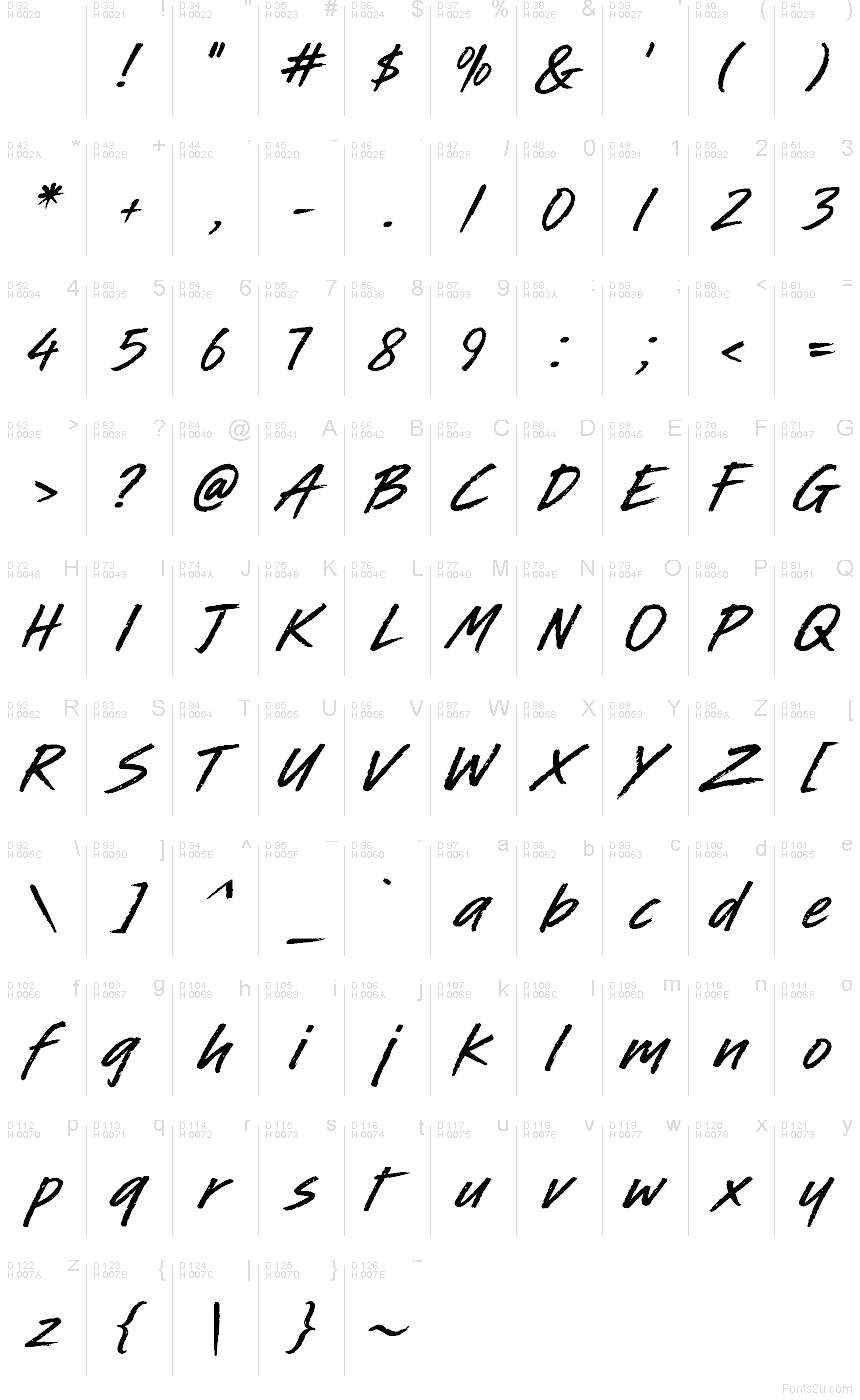
Style your Lipstick
Style Your Lipstick من تصميم CAT.B هو خط مجاني بأسلوب الفرشاة (Brush Script)، يتميز بضربات سريعة وملمس جاف ومكسور يمنح الحروف طابعاً خاماً وغير مصقول. تمنحه الحواف الخشنة والخطوط المتلاشية إحساساً يشبه الكتابة بأقلام الماركر أو فرش المكياج، مع تنوع كافٍ يجعل النص يبدو حيوياً وديناميكياً.
تتناسب هذه الحيوية التجميلية بشكل مثالي مع أغلفة أحمر الشفاه، وتصاميم الجمال، وعلامات البوتيك التجارية، وعناوين المدونات، وبطاقات الاقتباسات على وسائل التواصل الاجتماعي. ولأن أثر الفرشاة يبدو باهتاً قليلاً بدلاً من أن يكون لامعاً، فهو مثالي للملصقات اليدوية ولوحات الفعاليات، حيث تبدو اللمسة العفوية المكتوبة باليد أكثر طبيعية من الخطوط الكاليغرافية المتكلفة.